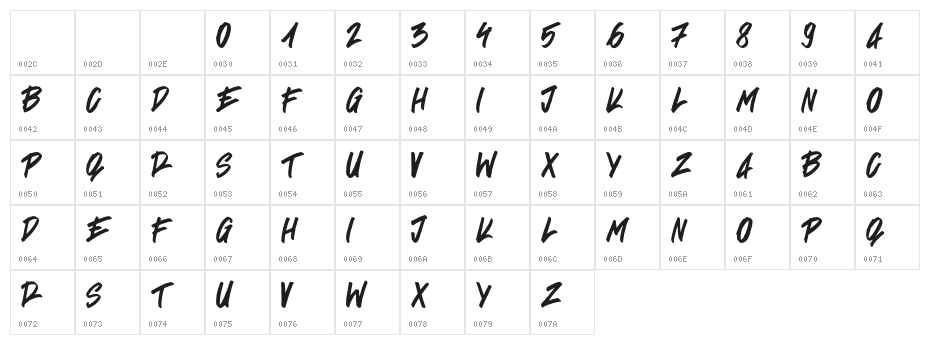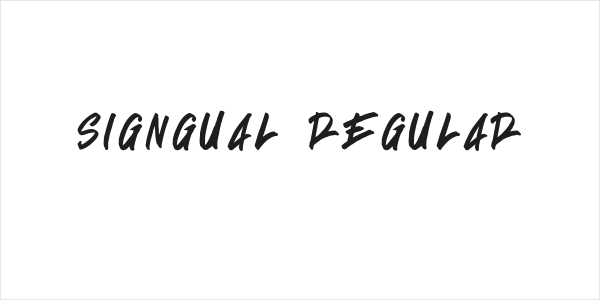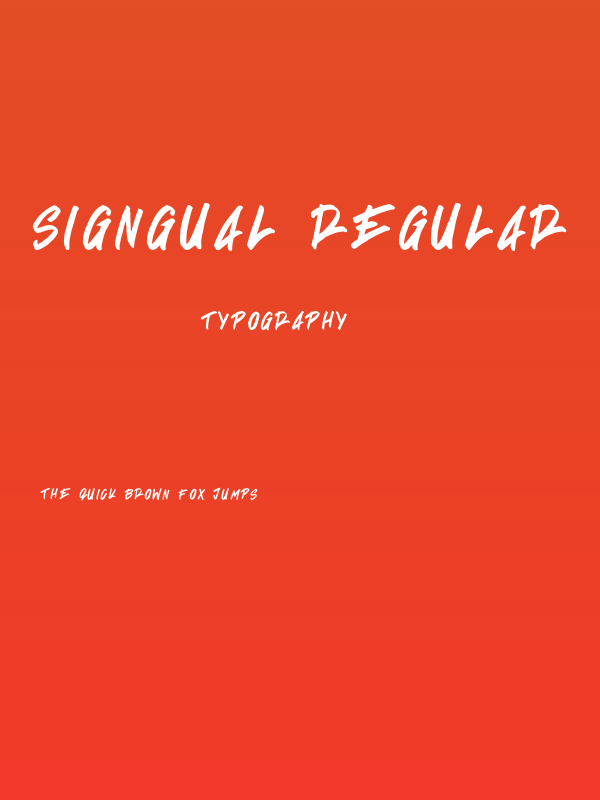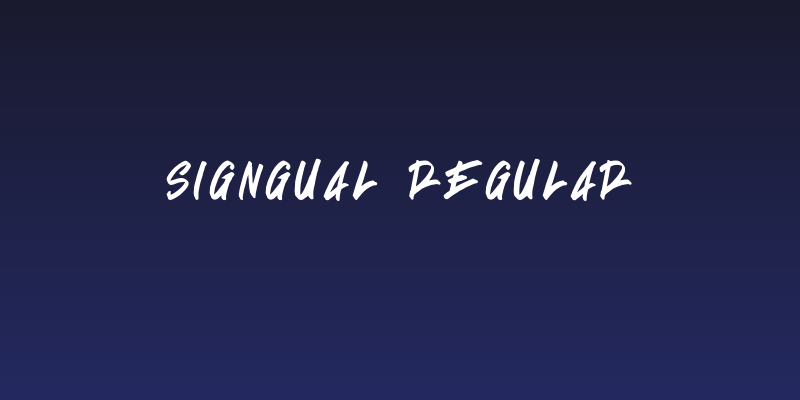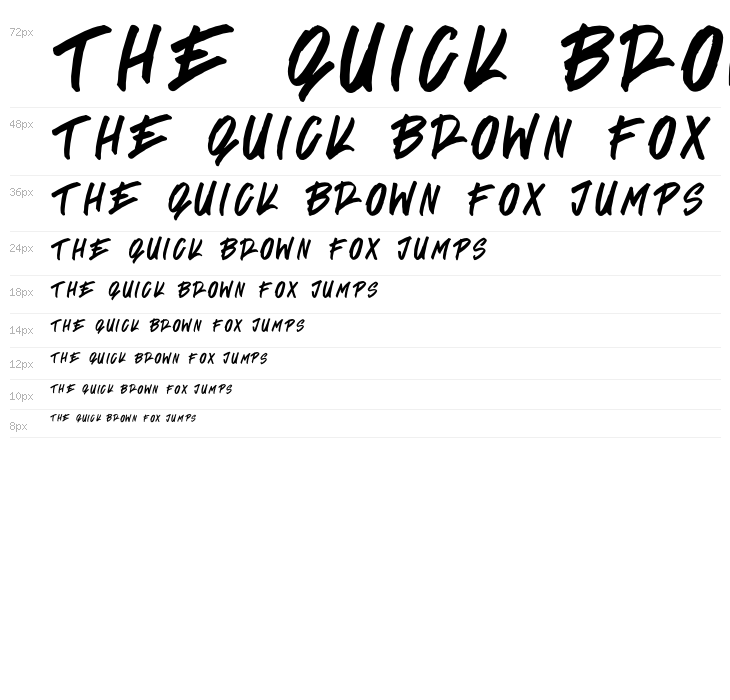
Signgual Regular Font
| Progetti proposti | Ideal for branding, social media graphics, posters, and invitations that require a personal and energetic touch. |